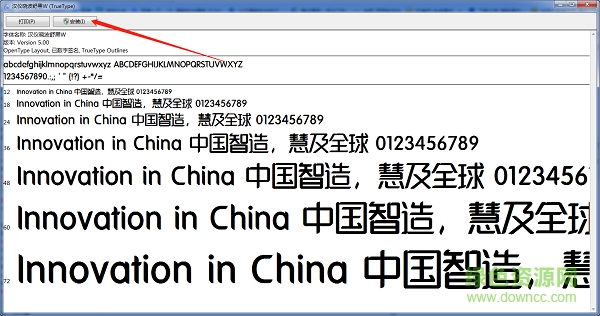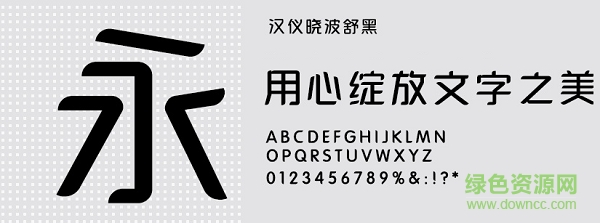
漢儀曉波舒黑體是同款字體較為圓潤的一款,字體筆鋒圓潤的設(shè)計能夠帶給用戶更多柔和感,簡約的豐富充滿現(xiàn)代時尚氣息,字體使用合理能夠更好的展現(xiàn)出你想要表達的特色,喜歡的用戶快來綠色資源網(wǎng)下載吧!
漢儀曉波舒黑W字體(HYXiaoBoShuHeiW.ttf)是一款由漢儀字體庫推出的創(chuàng)意中文字體,該字體本身字骨偏硬,橫豎撇捺均為直線,并且嘗試在筆畫細節(jié)上以圓角修飾,使字體的形式表達更加溫和,適用于多重文本的設(shè)計哦!